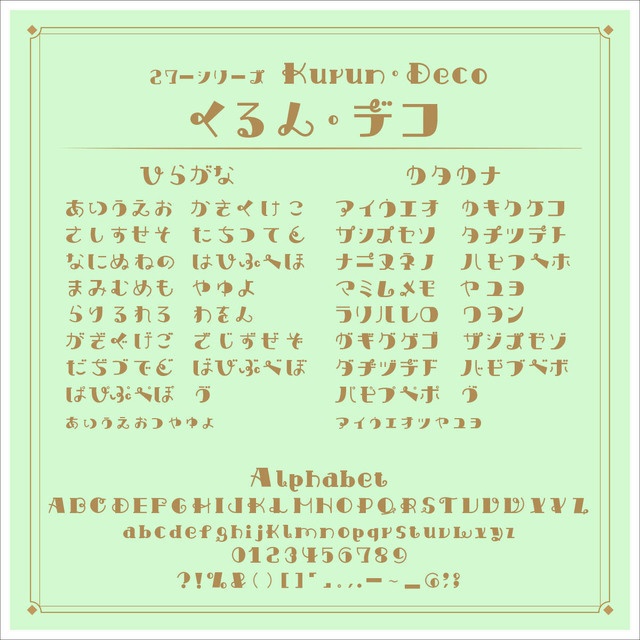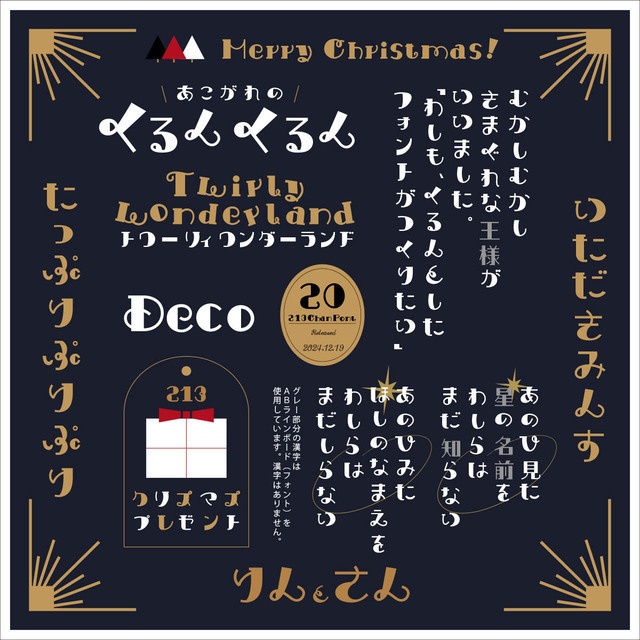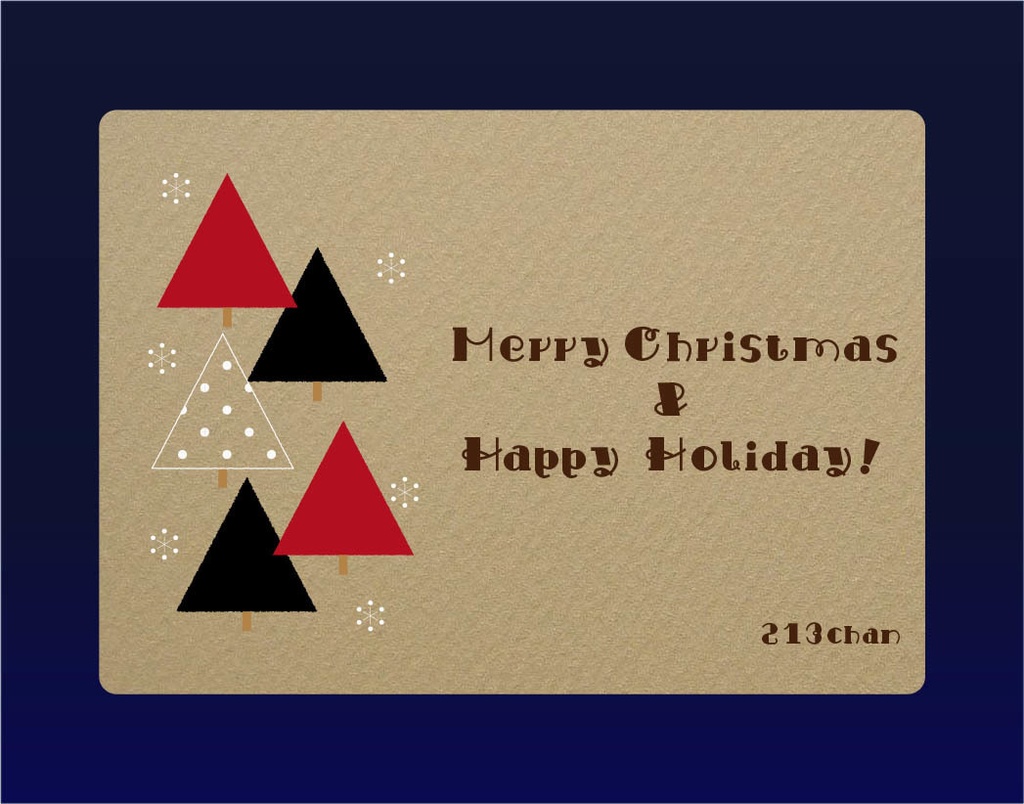
このくるん・デコ・フォントは213ちゃんが作った20個目のフォントになります。あこがれのくるん!とした書体に初チャレンジ! くるんとした愛嬌のあるフォントになりました。 20個目の記念フォントなのでぜひ使ってみてね。 通常:フリーダウンロード【商用可】 声援:有料DLで応援!¥100【商用可】 印刷物・ゲームやWeb、YouTubeのサムネイルやタイトルデザインなどにいかがでしょうか? 基本フリーですが、当フォントを利用した制作物などを、SNSで教えてくれると励みになります。 制作時のお気に入りポイントをnoteで記事にしています。 https://note.com/sweet_2727/n/n2a79e71300bb ぜひ遊びにきてね!スキ!お待ちしています。 【収録内容】欧文(大小)・ひらがな・カタカナ・数字・記号 【Readme】フォントご使用上の注意 ・フォントの著作権は、213ちゃんに帰属します。 ・可愛がってくださるとうれしいです。 ・無断転載・再配布は堅くお断りいたします。 ・DLしたフォントに起因する損害は補償致しかねますので予めご了承ください。 ・使用する際の不明点はお問い合わせ先にご連絡ください。答えられる範囲でお返事いたします。 英文 This font (213chan font) is a free OpenType font that can be used for commercial and personal web and print designs. Please take care of me. Font copyright belongs to 213chan. Unauthorized reproduction, redistribution, resale, and trademark registration of logos created using fonts is strictly prohibited. Please note that we cannot compensate for damage caused by DL fonts. Please note that we do not provide support regarding installation or usage.